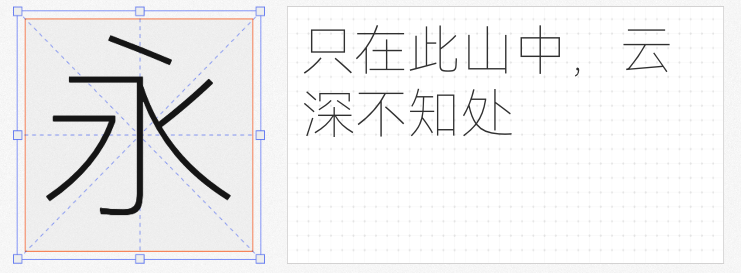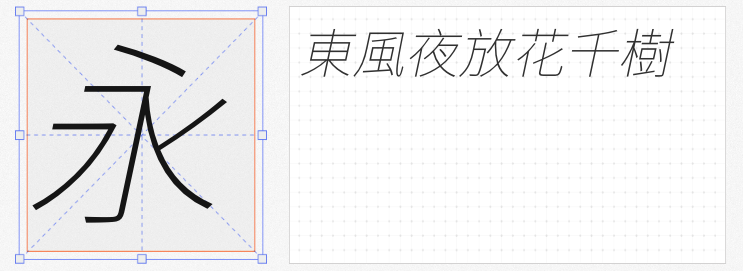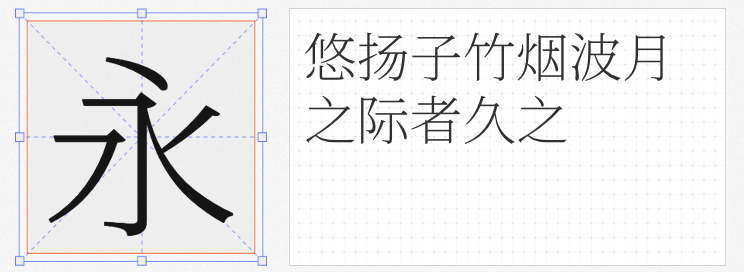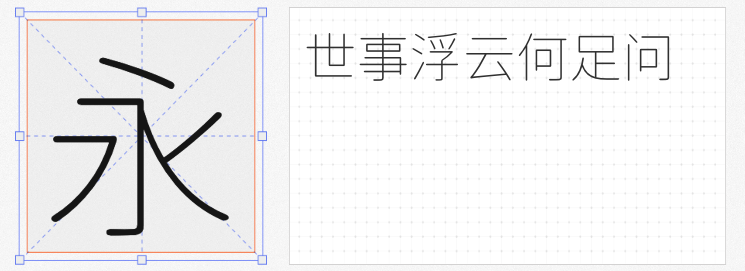
在数字设计的轻量化趋势中,极细字体正以克制而优雅的姿态重塑视觉语言。本文精选四款具备专业级设计品质的免费商用极细字体,从人文美学到功能创新,为设计师提供兼具实用性与艺术性的解决方案。
这款由华为联合汉仪字库打造的极细字体,在0.84:1的字宽比例中实现了功能性与人文性的完美融合。短笔画采用横平竖直的几何结构确保信息传达效率,长笔画则通过书法笔势的微妙弧度注入人文温度。其智能抗锯齿技术使字体在12px小字号下仍保持清晰轮廓,特别适合智能穿戴设备、移动端H5等小空间场景。在深色模式中,设计师可通过调整字符间距至0.02em,有效缓解极细字体的视觉压迫感。
突破传统倾斜字体的机械感,这款字体通过8°精准倾斜角构建出独特的速度美学。相较于后期倾斜处理,原生倾斜结构避免了笔画变形导致的识别障碍,其100,000字符的超大字库覆盖中日韩及拉丁语系。在动态海报设计中,搭配200%的行间距设置,可强化文字的流动感;与正体字组合使用时,建议保持150%的字间距以维持视觉平衡。
基于思源黑体的开放架构,这款字体通过0.5pt的圆角半径处理,创造出既保留黑体识别性又具备圆体亲和力的独特风格。其X字高与Y字高1:1.05的微妙比例,在长文本排版中展现出优异的阅读流畅性。在UI设计中,推荐搭配16px字号与1.5倍行高,既能保证移动端屏幕的清晰显示,又能通过圆角细节传递友好感。
作为昭源字体家族的极细成员,这款宋体通过0.3pt的衬线优化,在保持传统韵味的同时提升了屏幕显示适应性。其67,000字符的超大字库支持GB18030-2000标准,特别适合古籍数字化、文化类APP等需要大量生僻字的场景。在印刷品设计中,建议将字重提升至Regular配合使用,通过30%的灰度叠加可营造出精致的层次效果。